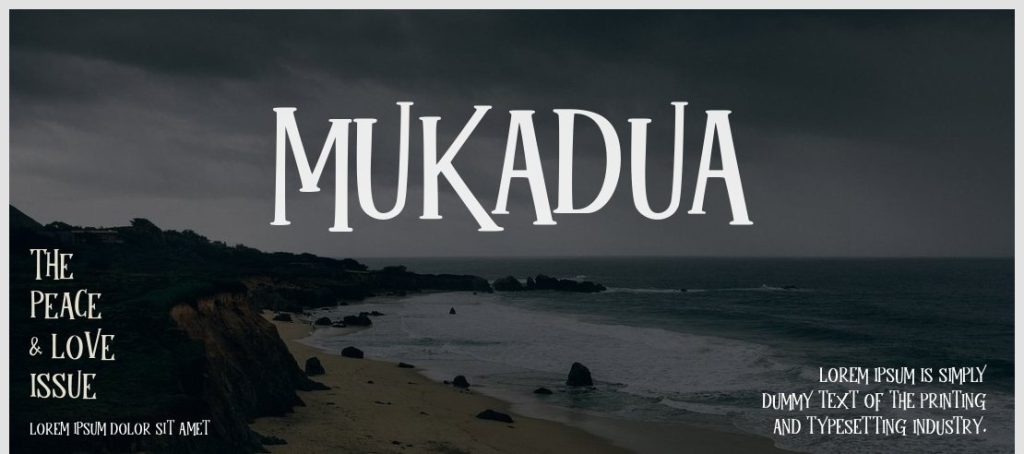
Tác giả: Letterhend
Font SVN Mukadua là một font chữ độc đáo và đầy sáng tạo thuộc bộ font SVN, được yêu thích bởi tính linh hoạt và phong cách hiện đại. Với sự kết hợp giữa các đường nét tinh tế và thiết kế gọn gàng, font chữ này rất phù hợp để sử dụng trong các dự án thiết kế đồ họa, thương hiệu hay quảng cáo. Không chỉ giúp nâng cao tính thẩm mỹ, font SVN Mukadua còn tạo nên sự chuyên nghiệp và nổi bật cho bất kỳ sản phẩm nào sử dụng nó. Nếu bạn đang tìm kiếm một font chữ độc lạ, mang lại sự khác biệt và cuốn hút, font SVN Mukadua chắc chắn là lựa chọn hoàn hảo.